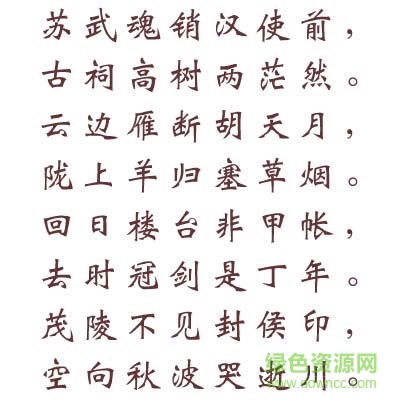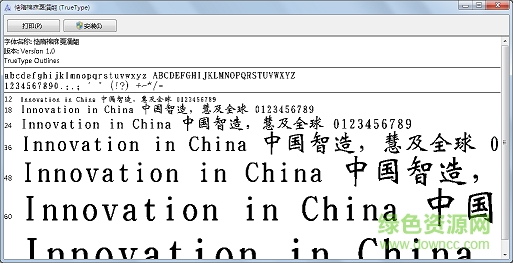
文鼎粗魏碑簡(jiǎn)是一款還算比較常用的魏碑字體,綠色資源網(wǎng)帶來的為ttf版,大家可以免費(fèi)下載,也可以點(diǎn)擊收藏,方便以后使用,而且該字體所變現(xiàn)的形式也落落大方,非常適合練習(xí)書法朋友使用,需要的就請(qǐng)來綠色資源網(wǎng)下載安裝。
這款字體美觀大方、簡(jiǎn)約干練,讓人有一種眼前一亮的感覺,適合應(yīng)用于藝術(shù)設(shè)計(jì)、平面宣傳設(shè)計(jì)、網(wǎng)頁設(shè)計(jì)、書法字帖等領(lǐng)域!